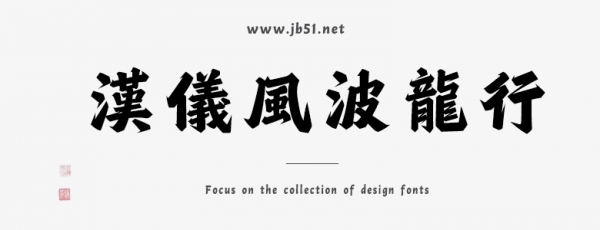
漢儀風(fēng)波龍行簡(jiǎn)體/繁體是由漢儀字庫出品,字體既保留了黑體粗壯有力的特征,也能展現(xiàn)出行楷字體的流暢自如的感覺,適合應(yīng)用于藝術(shù)設(shè)計(jì)、平面宣傳設(shè)計(jì)、網(wǎng)頁設(shè)計(jì),書法字帖等領(lǐng)域,需要的朋友可以前來本站下載。